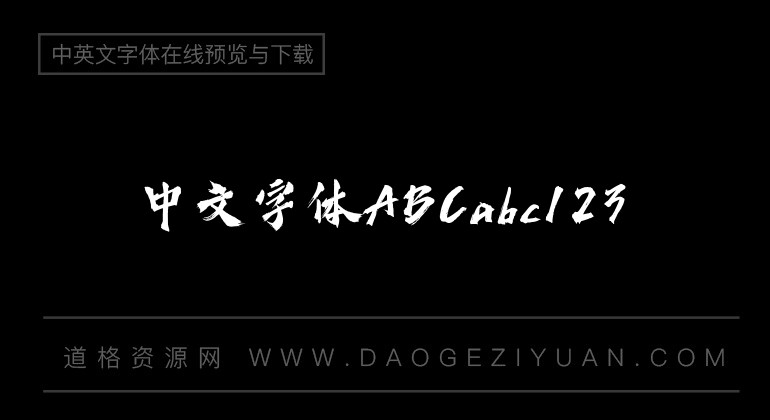
潮字社-凌渡鲲鹏-简字体是一款基于汉字技术的高端字体,它以高端的技术精湛的设计,打造出一款具有现代感的字体。它具有独特的折叠和拉伸特性,拥有极具个性的字形,可以满足不同的设计需求。它的字体设计更具有灵动性和流动性,更容易融入不同的文化背景中,以及更加精致的技术制作。文件名:ChaoZiSheLingDuPengJian-2.ttf
潮字社-凌渡鲲鹏-简是一款非常不错的手写艺术字体,具有很好的视觉感,适合于文化类的宣传设计、商业类品牌的广告和产品包装设计以及个性化文字排版等较多场景。